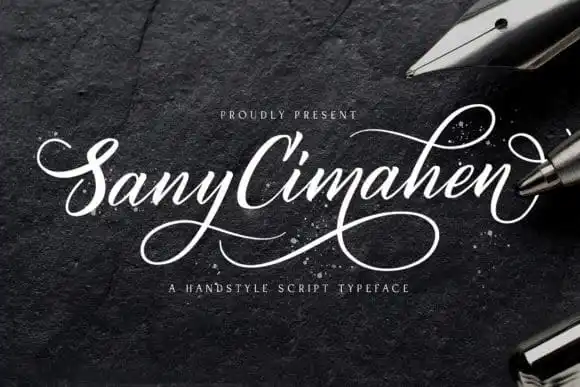
Sany Cimahen Calligraphy Font – Download Grátis
A fonte “Sany Cimahen Calligraphy Font” é uma exuberante escolha para designers apaixonados por letras elegantes e fluidas. Esta tipografia é especialmente perfeita para criadores de arte, oferecendo um estilo atraente que se adapta perfeitamente a qualquer projeto personalizado. Com o seu acabamento gráfico único e contemporâneo, essa fonte será sua nova paixão. Sua principal característica é uma combinação perfeita entre a elegância do script gráfico e a sensação de escrever com as próprias mãos. A PUA (Propriedades Unicode Avançadas) permite que você faça uso completo dos caracteres e das curvas fluidas desta fonte, sem esforço. Sua combinação perfeita entre estilo e praticidade torna-a uma escolha ideal para criar designs impressionantes. Engane-se em seu design e tente algo novo com esta fonte elegante.